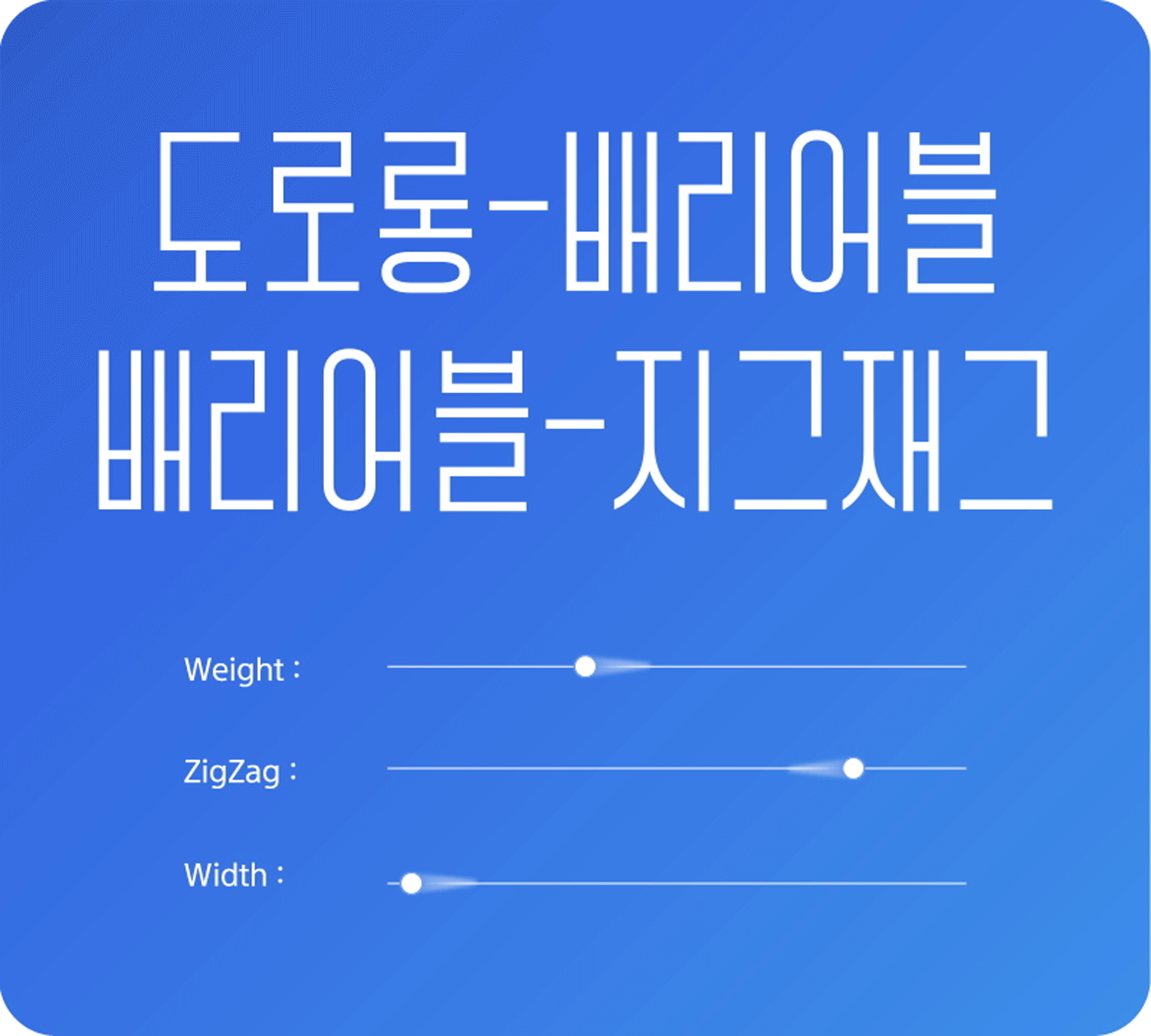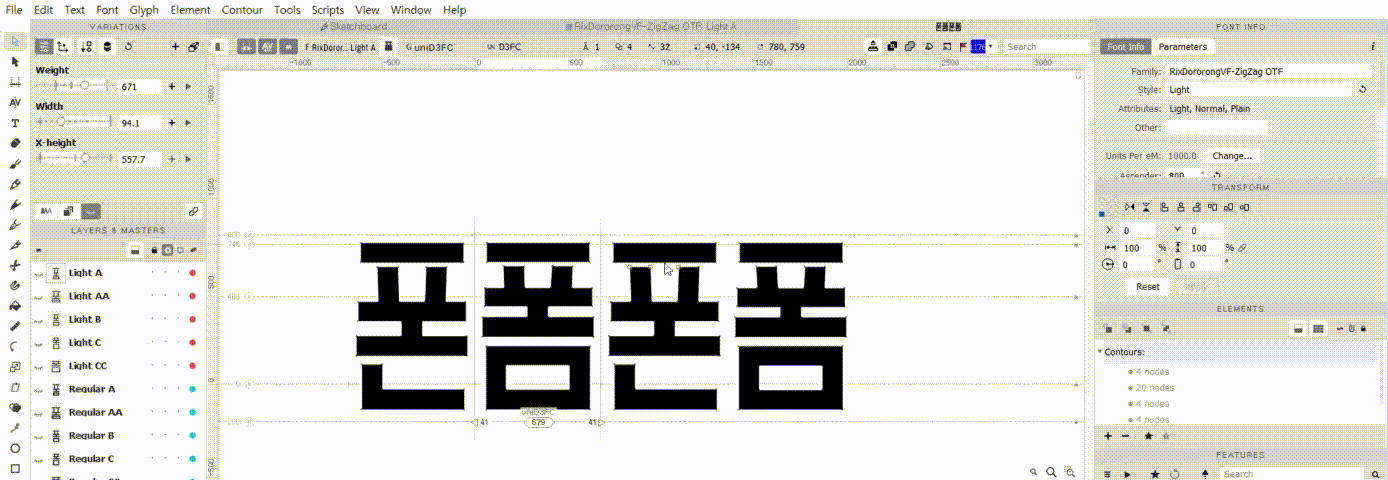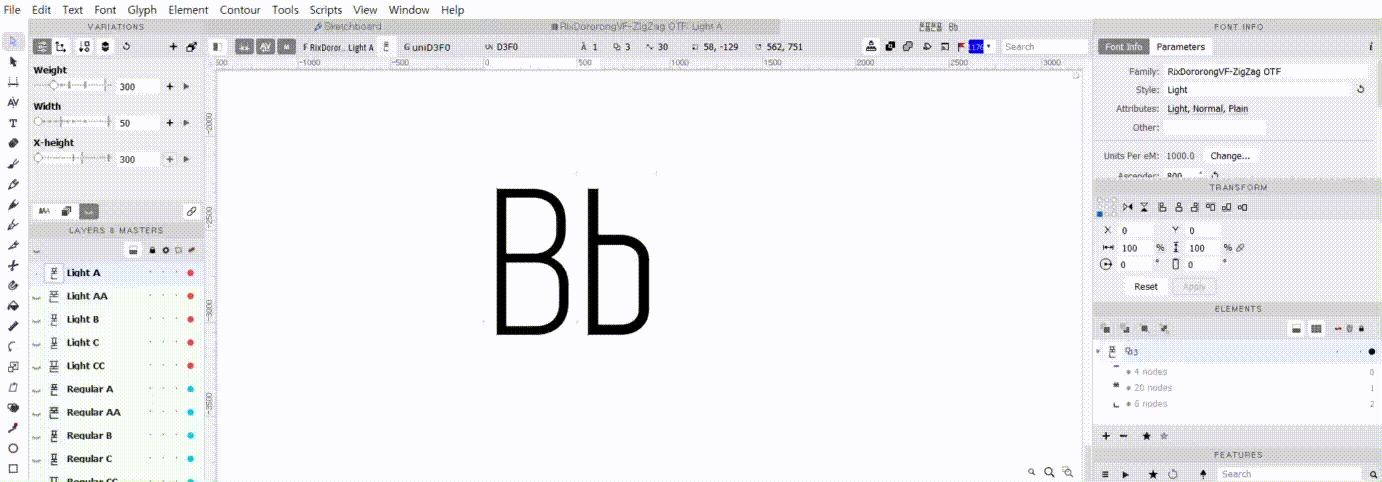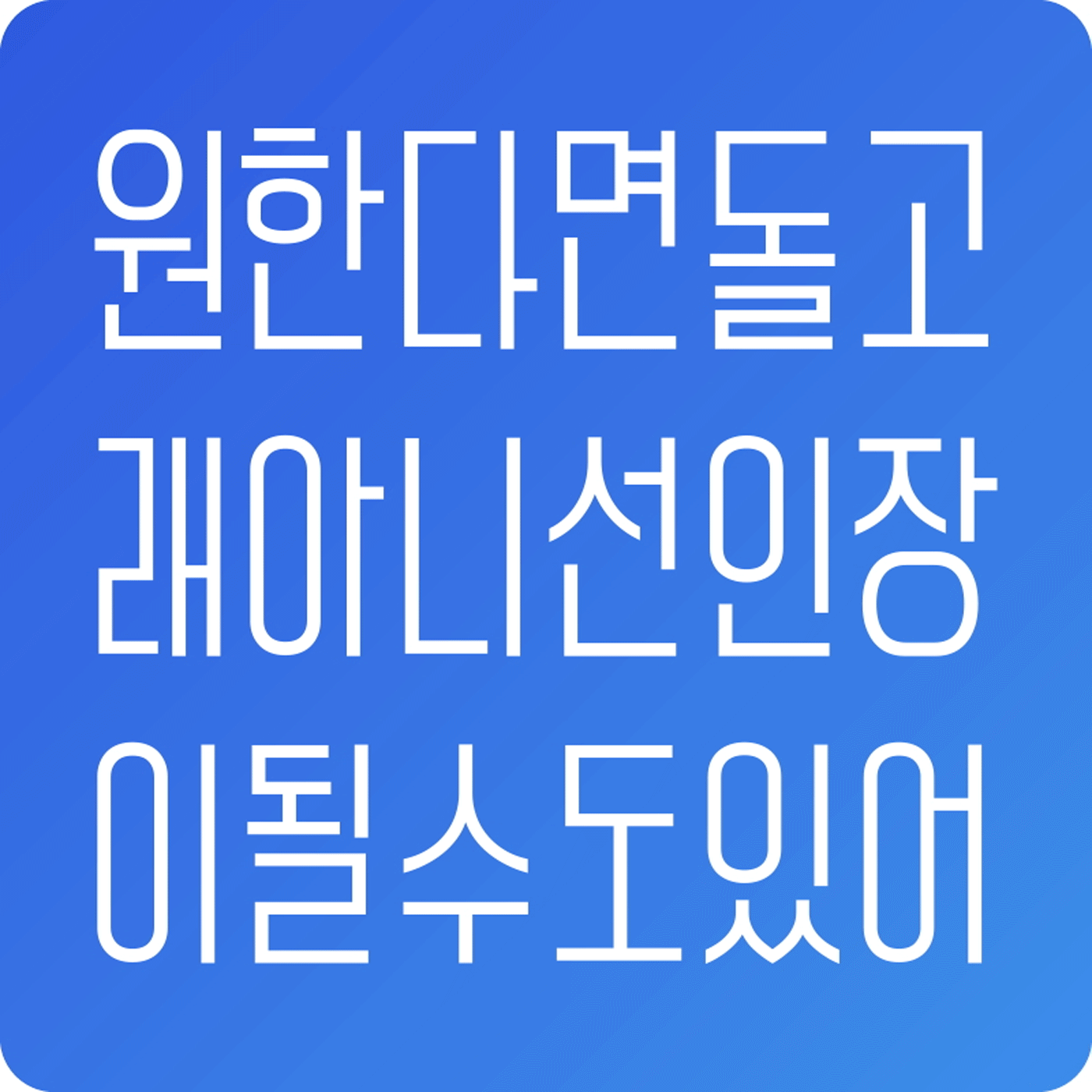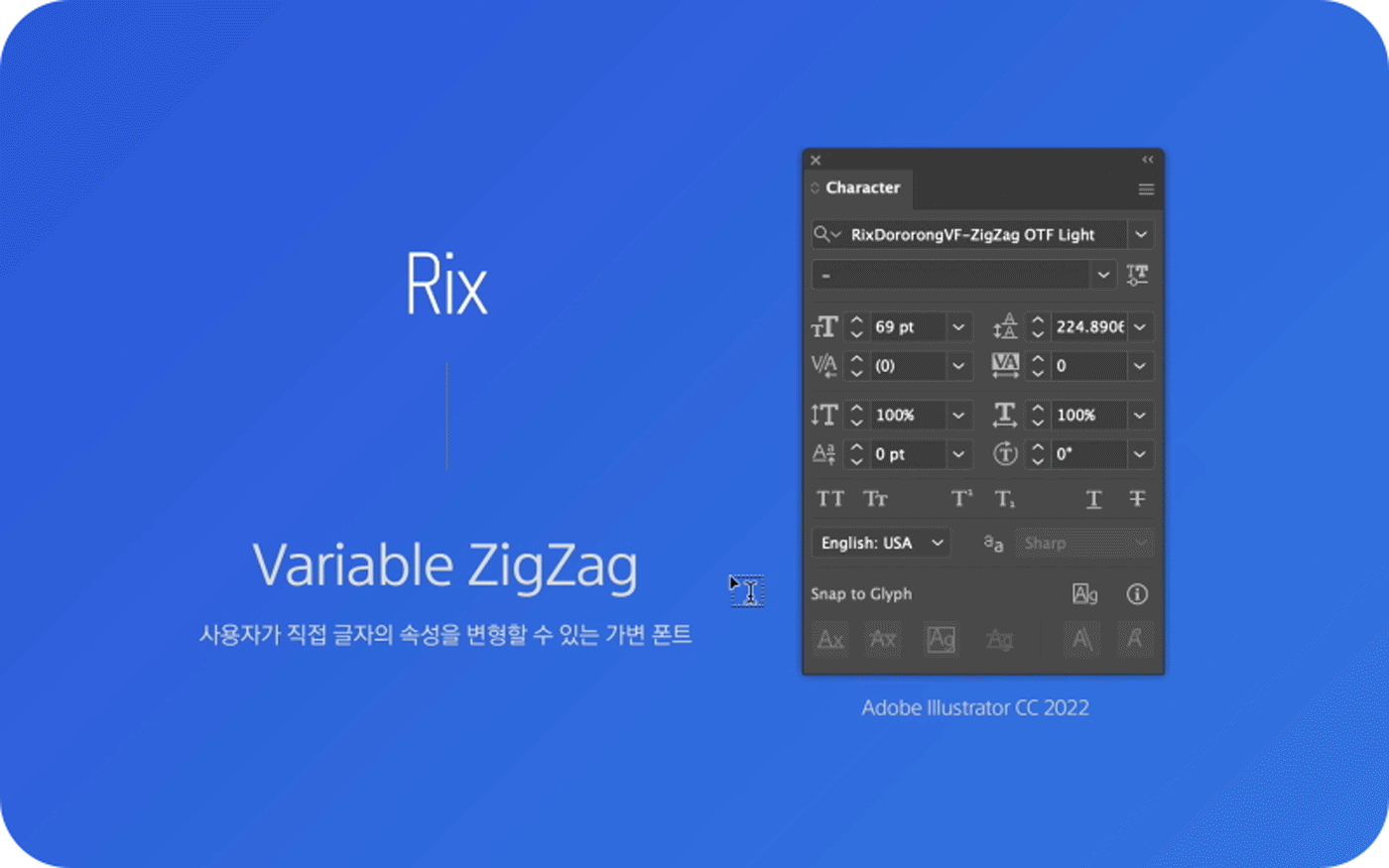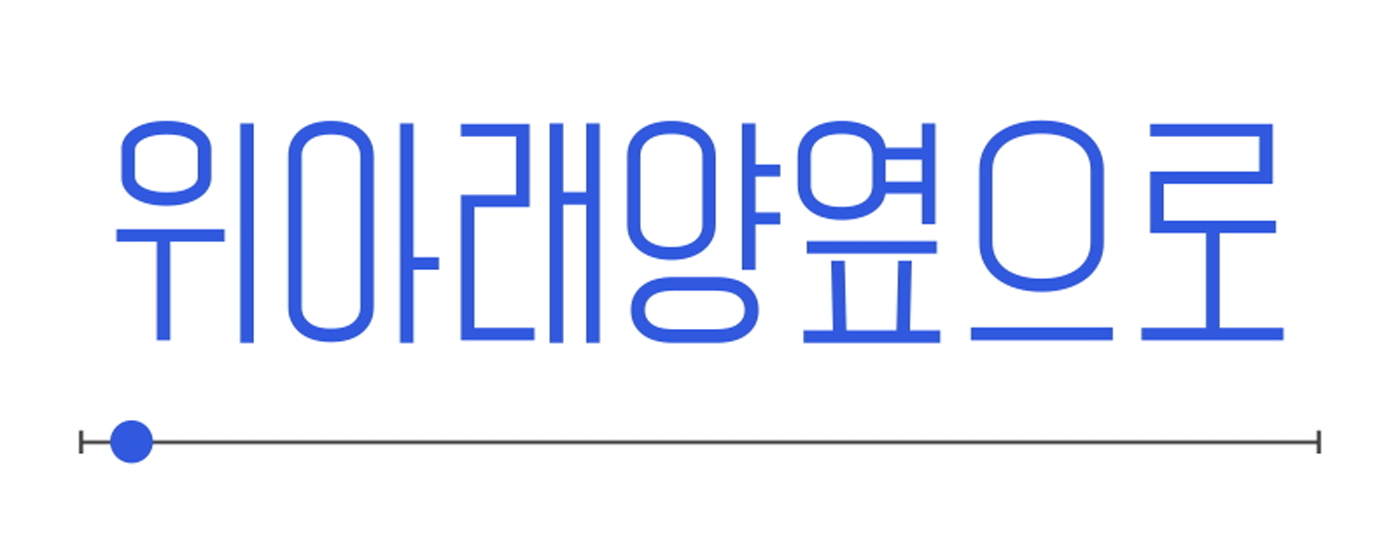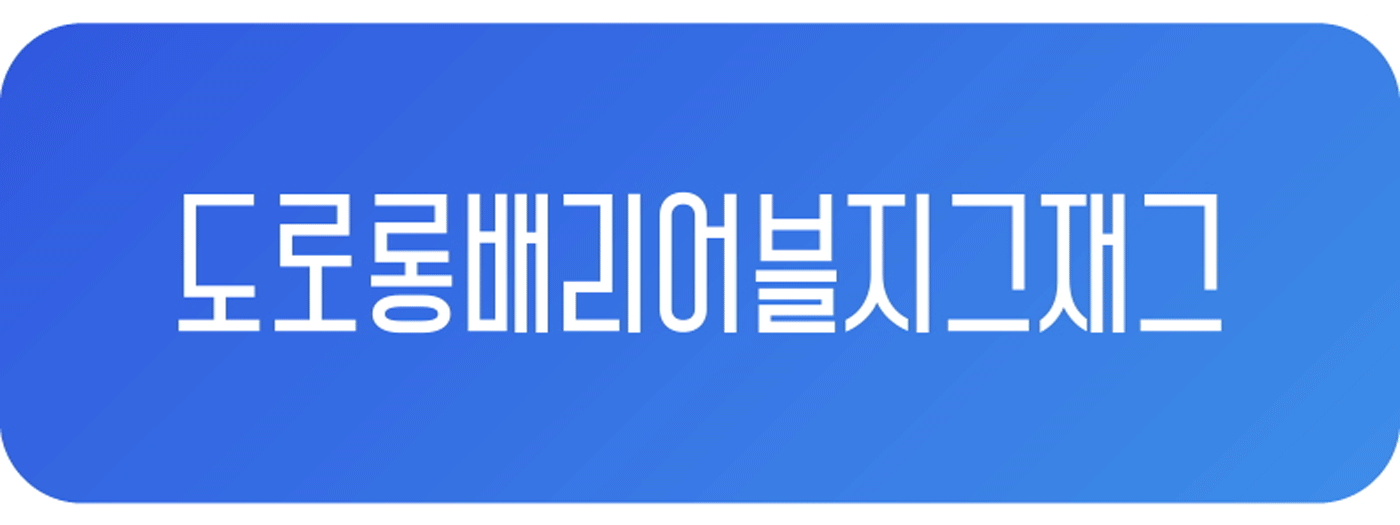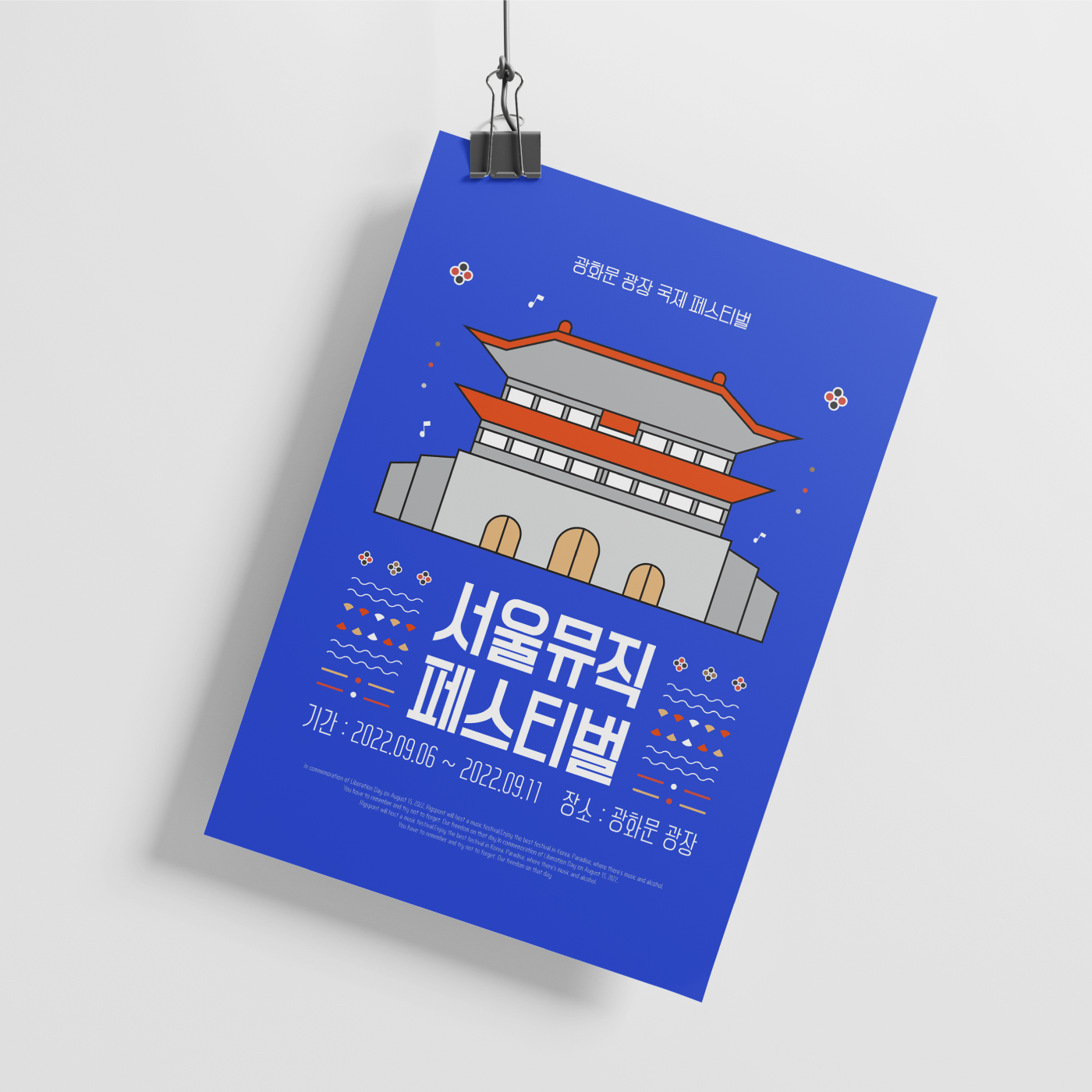
안녕하세요. 오늘은 지난달에 소개해 드린 도로롱 시리즈의 배리어블 폰트 Rix도로롱-VF-UpDown에 이어「Rix도로롱-VF ZigZag」를 데려왔습니다. 기존 도로롱배리어블-UpDown에서 재미있는 효과와 함께 업그레이드된 도로롱 배리어블 편의 완성 판이라고 볼 수 있겠습니다. 마.침.내 이번 배리어블 시리즈의 마침표를 찍은! 유현주 디자이너 먼저 만나보겠습니다 :)
안녕하세요, 유현주 디자이너님. 8월에 이어 다시 뵙게 되었네요!
네, 안녕하세요:) 진짜 진짜 도로롱 (아마도 진짜로) 마지막 시리즈로 인사드립니다.
Rix도로롱배리어블-ZigZag는 어떻게 제작되었는지 궁금해요.
8월에 출시한 Rix도로롱배리어블-Updown 기획 초기, 한 방향으로 움직이는 것도 재밌지만 좀 더 리듬감을 주면 좋을 것 같다는 생각이 들어 여러 변주를 주다가 탄생했습니다.
제작자로서 도로롱배리어블 UpDown과 ZigZag, 활용 꿀팁을 주신다면?
최근 Rix도로롱이 방송자막으로 종종 쓰이는 걸 봤는데 처음 기획했던 방향에 맞게 사용되고 있는 것 같아서 내심 기분이 좋더라고요. 배리어블 시리즈로 무게나 평을 조합해 더 다양한 연출을 할 수 있으니 앞으로도 자막이나 제목에 많이 노출되었으면 좋겠습니다!! (제발~)
Rix도로롱배리어블을 2탄까지 마무리하면서, 잘했다고 생각하는 것과 아쉬운 것이 있다면 무엇인가요?
사실 처음 기획할 때는 986자에 해당하는 약물까지도 배리어블로 진행하고 싶었는데, 아무래도 제약이 많다 보니 포기(?)하게 된 부분이 있는 것 같아 조금 아쉬움이 남았습니다만, 그래도 처음 출시한 폰트로 슬랩 세리프, 배리어블까지 다양한 시리즈를 연출하게 되어 기분이 좋습니다.
8월에 Rix도로롱배리어블-UpDown이 출시되고 “도로롱 시리즈를 라운드까지 내달라!”는 고객 요청이 쇄도했어요.(웃음) 혹시 가능성이 있을지?
저도 그 글 봤는데요..? 열심히.. 해보겠…습니다..? 사실 락배리어블처럼 라운드-도로롱-세리프까지 이어지는 배리어블도 생각은 해보았습니다만,, 당분간 도로롱을 조금 놔주고 싶어요..(웃음) 아 그리고 조만간 도로롱배리어블 시리즈의 영문에 업데이트가 있을 예정입니다! 많관부 부많관!
디자이너님이 처음 Rix도로롱을 출시한 지 벌써 1년이 되어가더라고요! 폰트 디자이너로서의 1년을 돌아보면 어떤지, 또 앞으로 어떤 계획이 있으신지 궁금해요.
제가 처음 Rix도로롱 출시 인터뷰를 할 때도 배리어블에 흥미가 생겼다고 답변했더라구요. 기획은 당시와 달라졌지만 흥미를 잃지 않고 출시하게 되어 스스로 대견(?)하다고 생각하고 칭찬을 많이 해주었습니다. 이후에 또 재밌는 기획으로 찾아 뵐 수 있으면 좋겠습니다~!
ZigZag로 더 재미롭게!
도로롱배리어블-UpDown에서 글자의 굵기, 너비, 무게 중심을 자유롭게 조정하여 설정할 수 있었는데요. Rix도로롱배리어블-ZigZag는 무게 중심에 변형을 준 배리어블 폰트입니다. 서체의 무게 중심이 앞뒤로 다르게 적용이 되며, 위아래 지그재그로 움직이는 변주를 주어 더욱 재미있는 표현이 가능해졌어요.
글자의 두께 Weight, 너비 Width, 무게 중심(X-height)을 원하는 대로 세밀하게 조절해 보세요!
깔끔하고 모던한 서체 스타일, 속공간이 시원한 형태의 도로롱배리어블. 굵기도 본문용에 적절한 얇은 두께부터 제목용에 사용하기 좋은 두꺼운 굵기까지 표현할 수 있어 다양하게 활용할 수 있습니다.
물론 너비도 자유롭게 배리어블 할 수 있기 때문에 모던하게 때론 레트로한 느낌으로 표현할 수도 있습니다.
| 이렇게 활용해 보세요
깔끔한 디자인, 두꺼운 굵기를 활용해 포스터나 배너 등 타이틀에, 얇은 굵기로는 설명 텍스트에 사용하기 좋습니다. 너비도 조절해서 사용하면 하나의 폰트로 제목과 본문에 모두 사용할 수 있어 쉽고 편하게 디자인할 수 있어요✍️
무게 중심이 지그재그로 적용되어 있어 짧은 글도 단조롭지 않고 디자인적으로 연출할 수 있습니다. UI나 UX 디자인, 영상 썸네일, 자막 등에 다양하게 활용하기 좋아요.